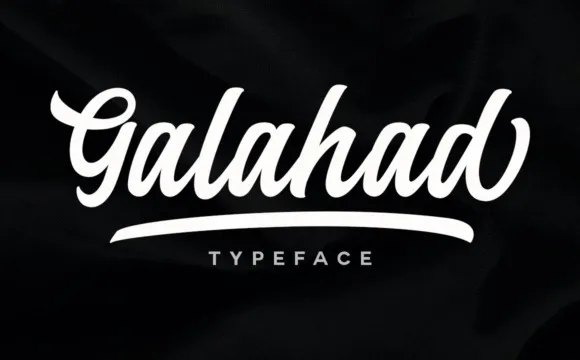
A Galahad Font é uma opção irresistível para qualquer designer buscando uma fonte script charmosa que se destaca. Criada pelo talentoso RasdiType, esta font adquire um toque autêntico e suave devido à sua textura realista. É perfeitamente adaptável a diversos estilos, desde os mais formais até os mais criativos. A Galahad leva uma dinâmica força e confiança que certamente se adequará perfeitamente ao seu design. Um dos seus principais recursos é ser PUA (Unicode Private Use Area) codificada, o que significa que você pode facilmente acessar todos os belos gílitos e swashes com uma grande liberdade. A Galahad é a escolha ideal para quem busca uma fonte escrita de alta qualidade em seu projeto, seja um livro infantil ou uma capa de revista fashion. Experimente-a e veja por si mesmo o poder deste design criativo e sofisticado.